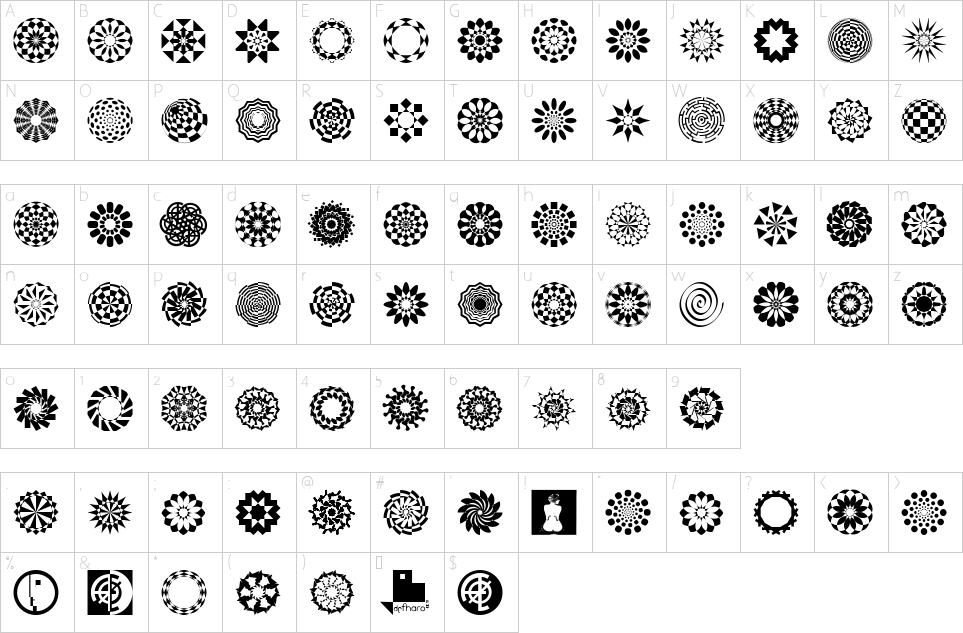
Wach Op-Art Font
Descubra a criatividade vibrante e alegre com Wach Op-Art Font! Essa elegante família de letras foi cuidadosamente projetada por deFharo, oferecendo uma gama de opções para tornar qualquer projeto único e divertido. Com seu design artístico e abrangente alcance, essa fonte é perfeita tanto para títulos chamativos quanto para texto mais sofisticado. Se você está procurando adicionar um toque de arte ótica a seus projetos digitais ou impressos, Wach Op-Art é uma escolha inteligente. Baixe já e veja como essa fonte pode transformar seu trabalho em algo realmente especial. Com 23.503 downloads desde sua disponibilização, temos certeza de que você irá apreciar o poder criativo desta fonte.